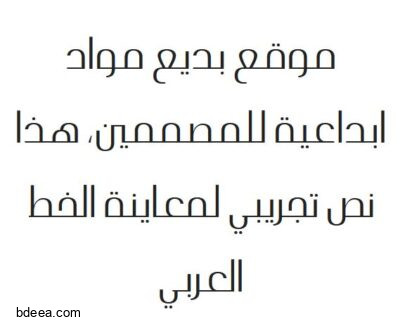
تحميل خط عربي اويا OYA Bold font download
تحميل خط عربي اويا OYA Bold font download يضيف لمسة فنية رائعة الى التصاميم العربية والمطبوعات والعروض التقديمية بالكلمات العربية والارقام بشكل مميز يمكنك تثبيته على جهازك والبدء باستخدامه في برامج التصميم
يتميز بالخط بالمرونة والخفة والشكل الانيق في الكتابة والحروف يمكن معاينته وتجربة استخدامه ليضيف لك تميز الى تصاميمك